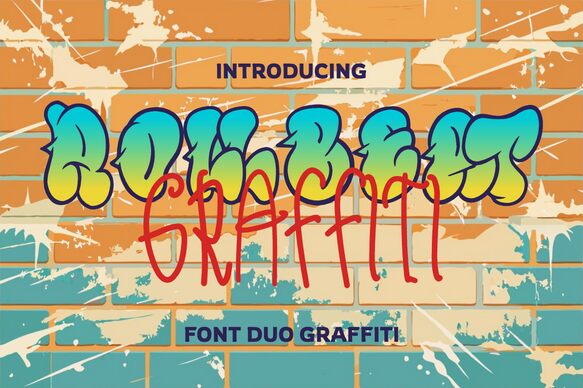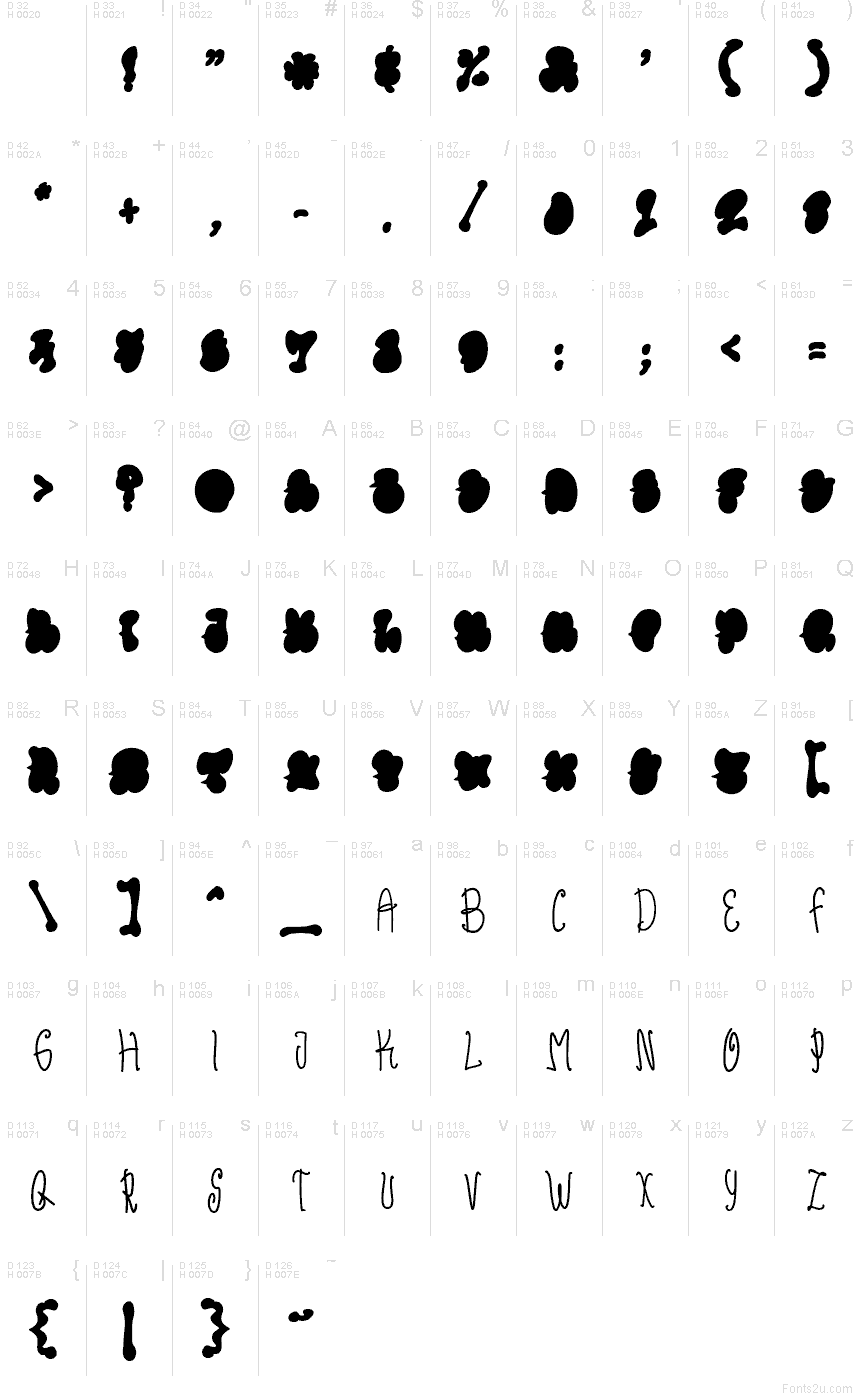
Rollbeat Graffiti Fill von Shanaf Studio ist eine kostenlose Graffiti-Tag-Schrift mit lockeren Marker-Strichen, bulligen Bubble-Formen und geschwungenen Loops, die direkt von der Wand stammen könnten. Die Buchstaben kombinieren drahtige Vertikale mit abgerundeten, gefüllten Formen, was für einen Rhythmus sorgt, der sich schnell, verspielt und ein wenig ungehobelt – statt durchgestylt – anfühlt.
Dadurch eignet sich diese kostenlose Schrift perfekt für Streetwear-Designs, Musik-Artwork, Plakat-Titel, Zine-Cover, Skate-Branding und Social-Media-Header, bei denen es auf einen handgezeichneten Look ankommt. Sie funktioniert am besten in kurzen Textpassagen – etwa für Titel, Cover-Lines und markante Wortmarken –, da die verspielten Details und die unebene Dynamik selbst wenigen Buchstaben sofort jede Menge Attitüde verleihen.